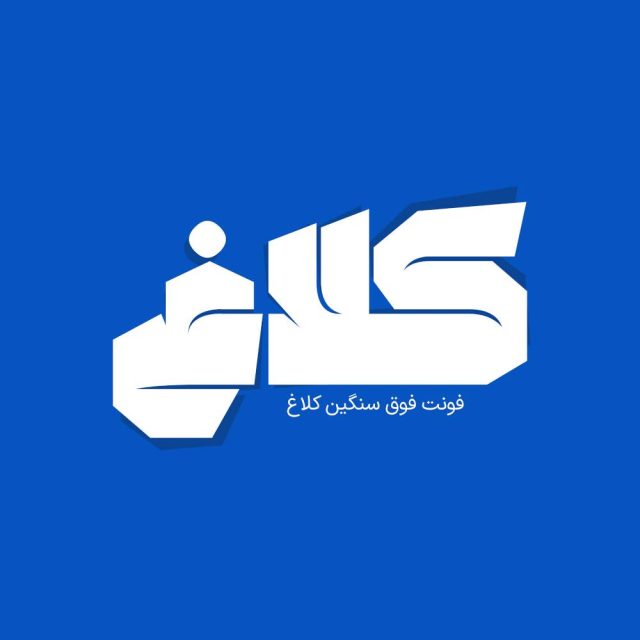
فونت فارسی کلاغ Kalagh Font
فونت فارسی کلاغ یک فونت متفاوت و زیبای فارسی می باشد که در وزن بولد طراحی شده است، فونت فارسی کلاغ مناسب استفاده در عناوین و…
فونت فارسی کلاغ یک فونت متفاوت و زیبای فارسی می باشد که در وزن بولد طراحی شده است، فونت فارسی کلاغ مناسب استفاده در عناوین و تیترها و جملات نسبتا طولانی و هم طراحی انواع لوگوتایپ، تکست گرافی و استفاده در طراحی های خاص می باشد.
پیشنمایش و نمونه تایپ های فونت کلاغ